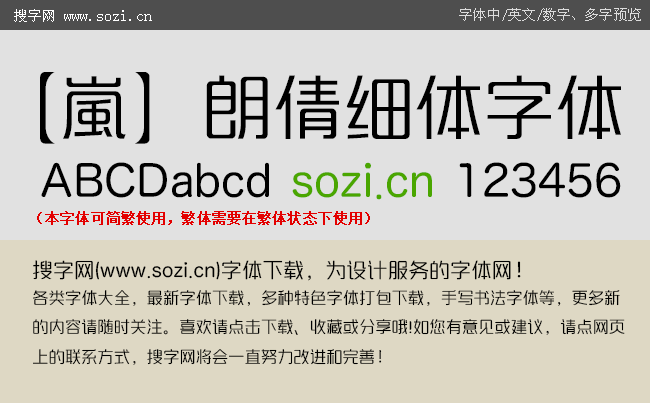
朗倩細(xì)體字體
搜字網(wǎng)給大家提供一款朗倩細(xì)體字體手機(jī)中文字體下載。朗倩細(xì)體字體筆畫(huà)簡(jiǎn)潔、粗細(xì)分明,中正不失圓潤(rùn),曲線流暢,結(jié)構(gòu)穩(wěn)重大方,整套字形柔和飽滿,如玉似珠,字形姿態(tài)橫生,結(jié)構(gòu)疏朗飄逸。特別適合喜歡手機(jī)個(gè)性的朋友在手機(jī)上安裝使用。